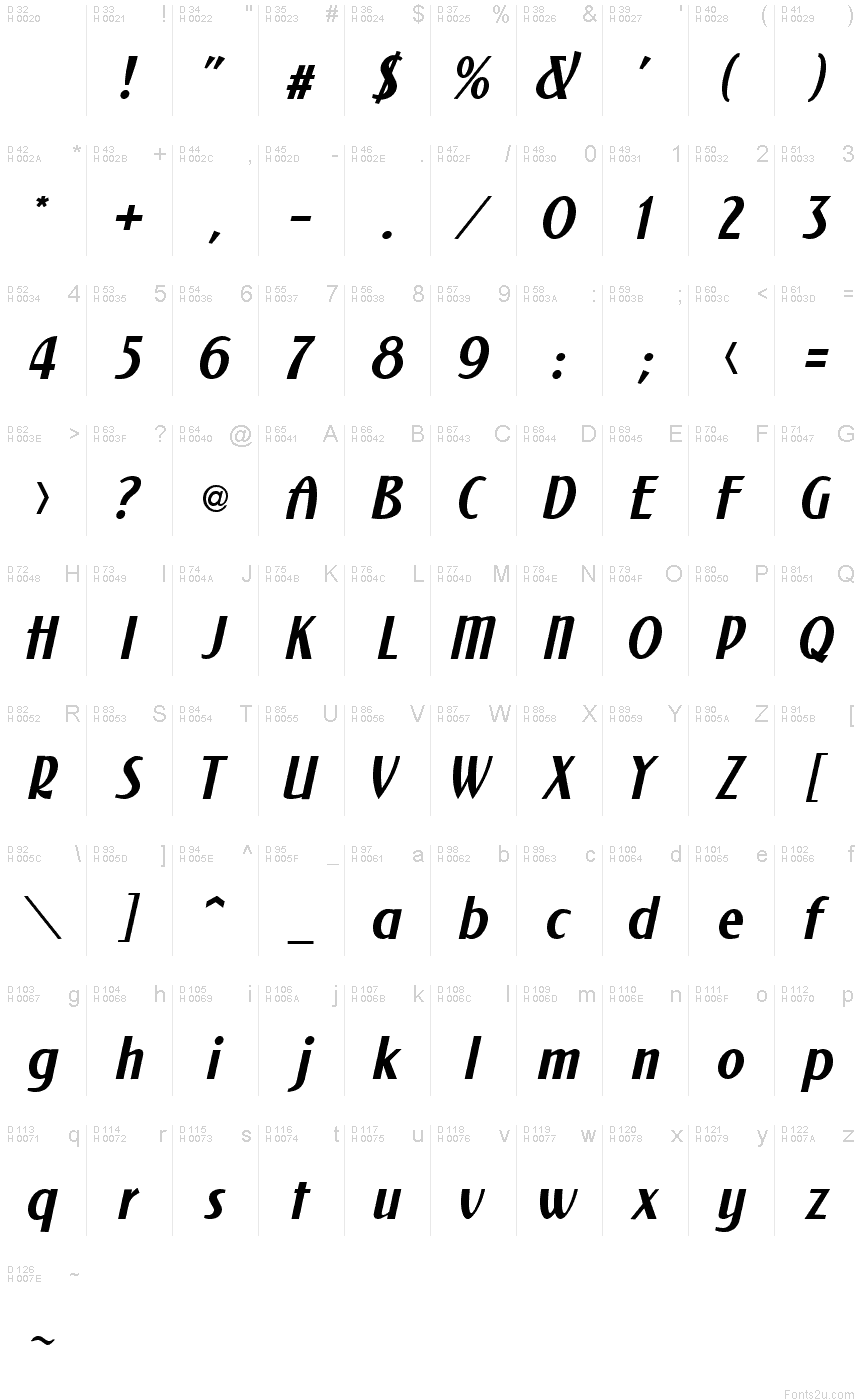
New Forum Italic autorstwa Thomasa E. Harveya to darmowy, retro krój typu display, wyróżniający się mocno pochyloną sylwetką oraz długimi, wąskimi literami. Przechył w przód i płynne krzywe sprawiają, że wzrok naturalnie przesuwa się między słowami, nadając pismu energiczny i smukły charakter.
New Forum Italic świetnie sprawdza się w logotypach, nagłówkach plakatów, okładkach magazynów, etykietach produktów, ulotkach wydarzeń oraz krótkich tekstach reklamowych lub bannerach, które wymagają szybkiego, ukośnego akcentu. Kompaktowa dynamika tego kroju dodaje brandingowi i projektom redakcyjnym wyraźnego tempa, nie przytłaczając strony.